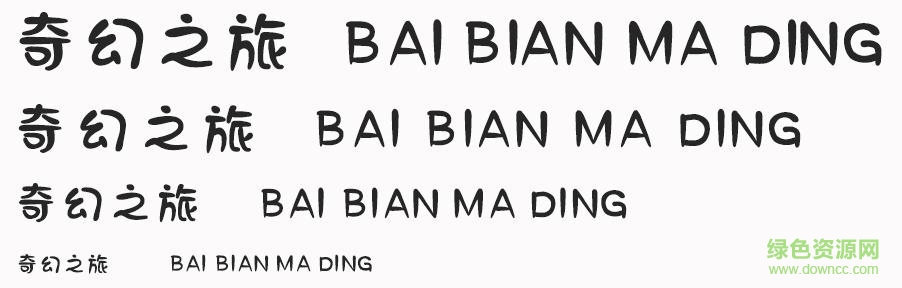
印品百變馬丁字體是一款有印品字庫開發(fā)的動(dòng)畫字體,喜歡看百變馬丁的朋友們不要錯(cuò)過了,字里行間都是馬丁的氣息。還等什么,快來綠色資源網(wǎng)踴躍下載使用!
印品字庫攜手今日動(dòng)畫IP百變馬丁,共同打造的首款同名動(dòng)畫字體上線啦!充滿童趣的字形設(shè)計(jì),處處體現(xiàn)《百變馬丁》突出的人物形象,為的就是讓粉絲有種見字如面的既視感??靵砗婉R丁開啟一段不一樣的奇幻之旅吧~